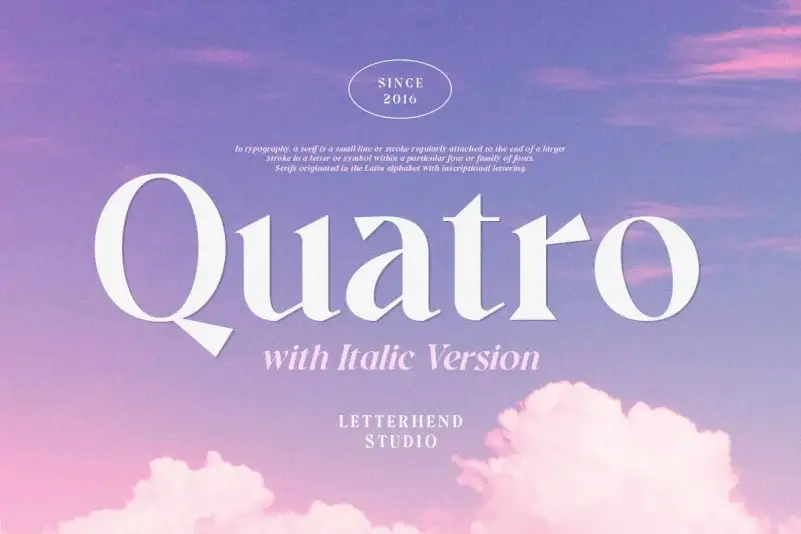
Quatro Serif Font – Fonte Grátis
Quatro Serif Font
A Quatro Serif Font é uma elegante tipografia serif inspirada no famoso logotipo minimalista. Desenvolvida para atender a necessidade formal e sofisticada, esta família de letras perfeita para aplicações como logos, convites, selos, marcas de embalagens, revistas, livros, cartões de saudação ou casamentos, produtos de beleza, materiais de escritório e até mesmo anúncios. Através de seu design delicado e clássico, a Quatro Serif Font se adequa perfeitamente para qualquer necessidade formal que exija elegância e profissionalismo.